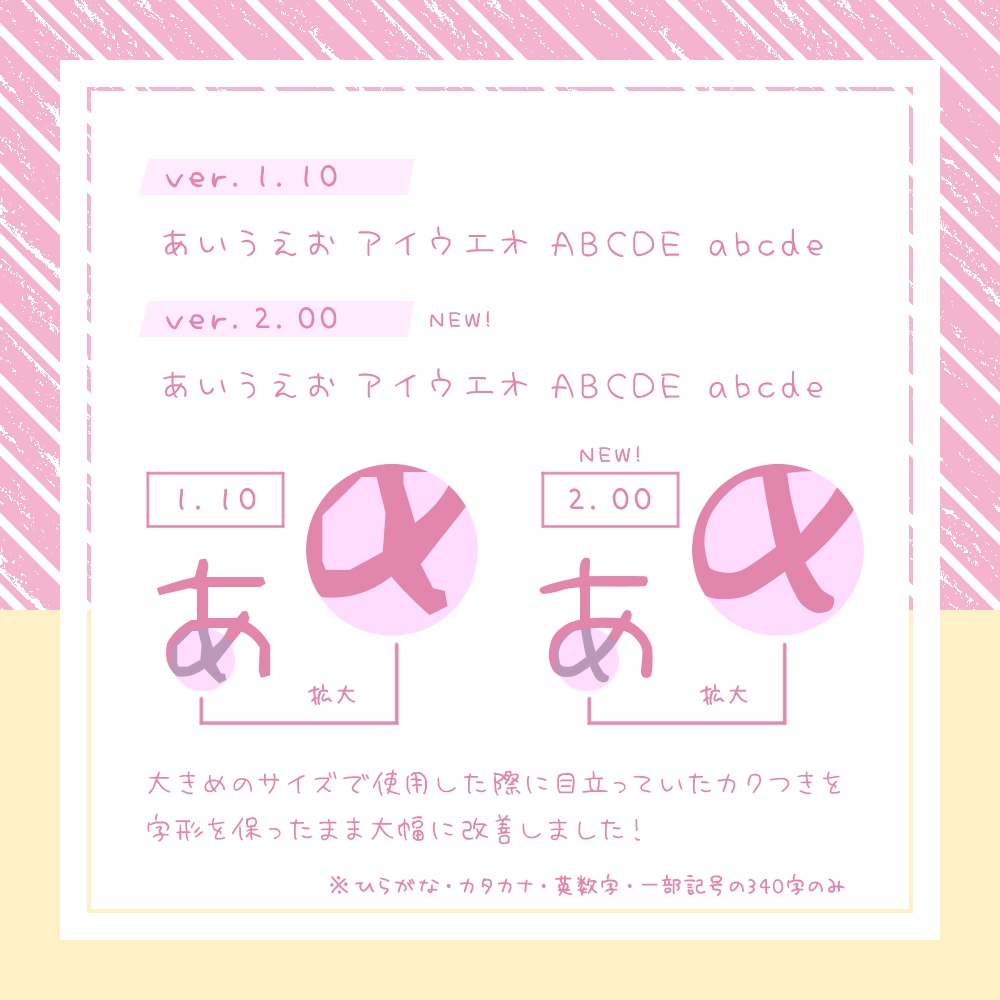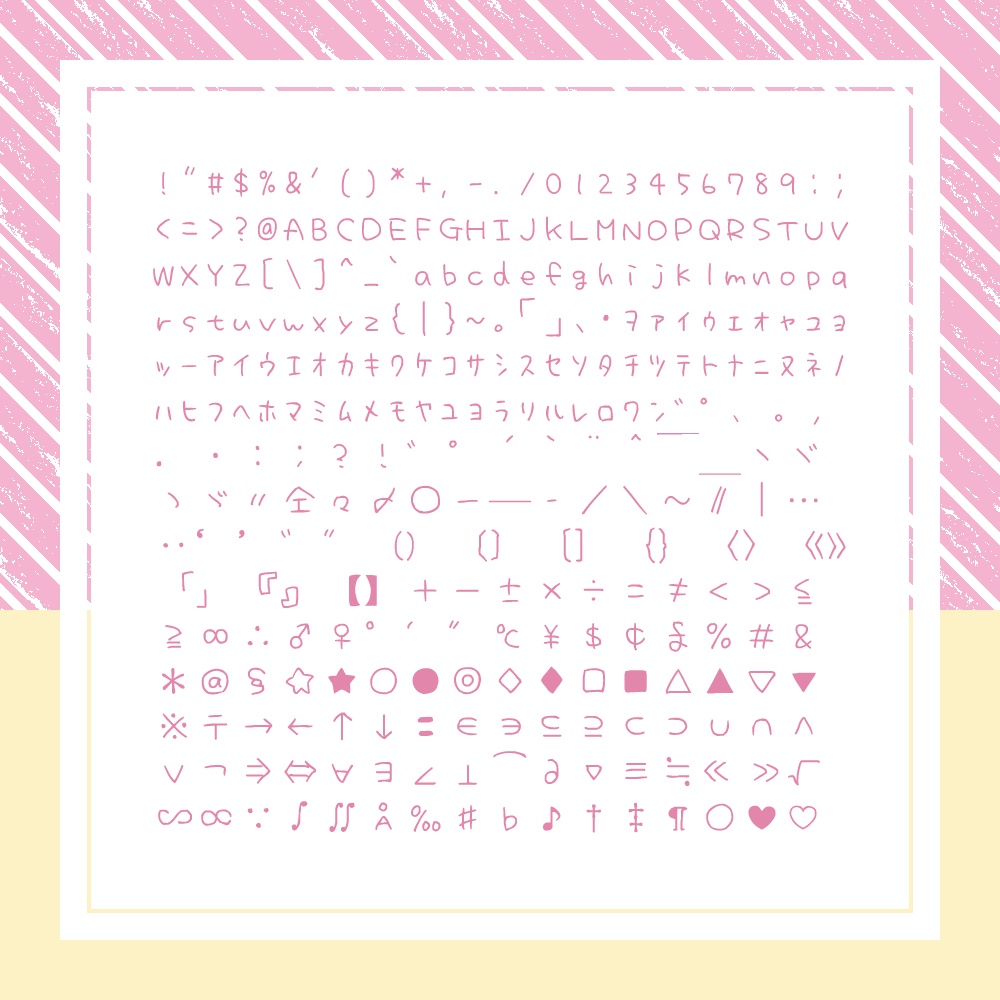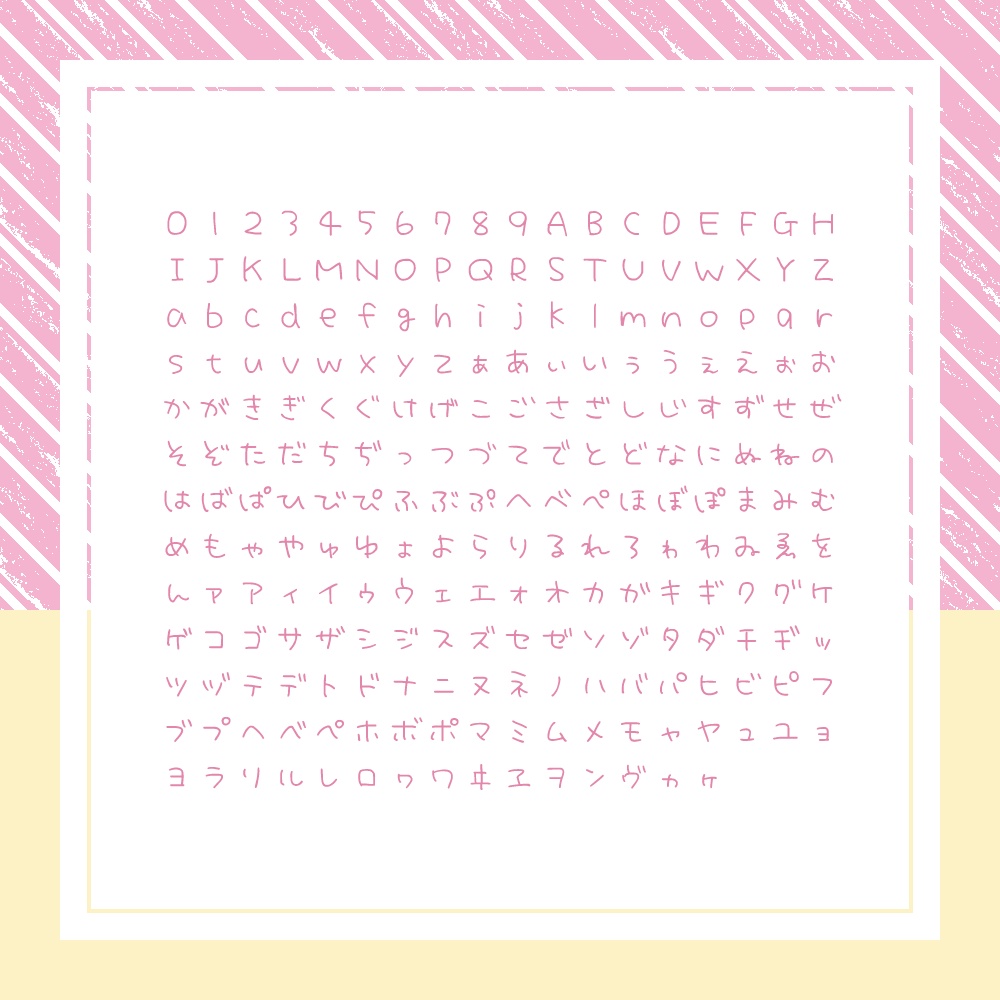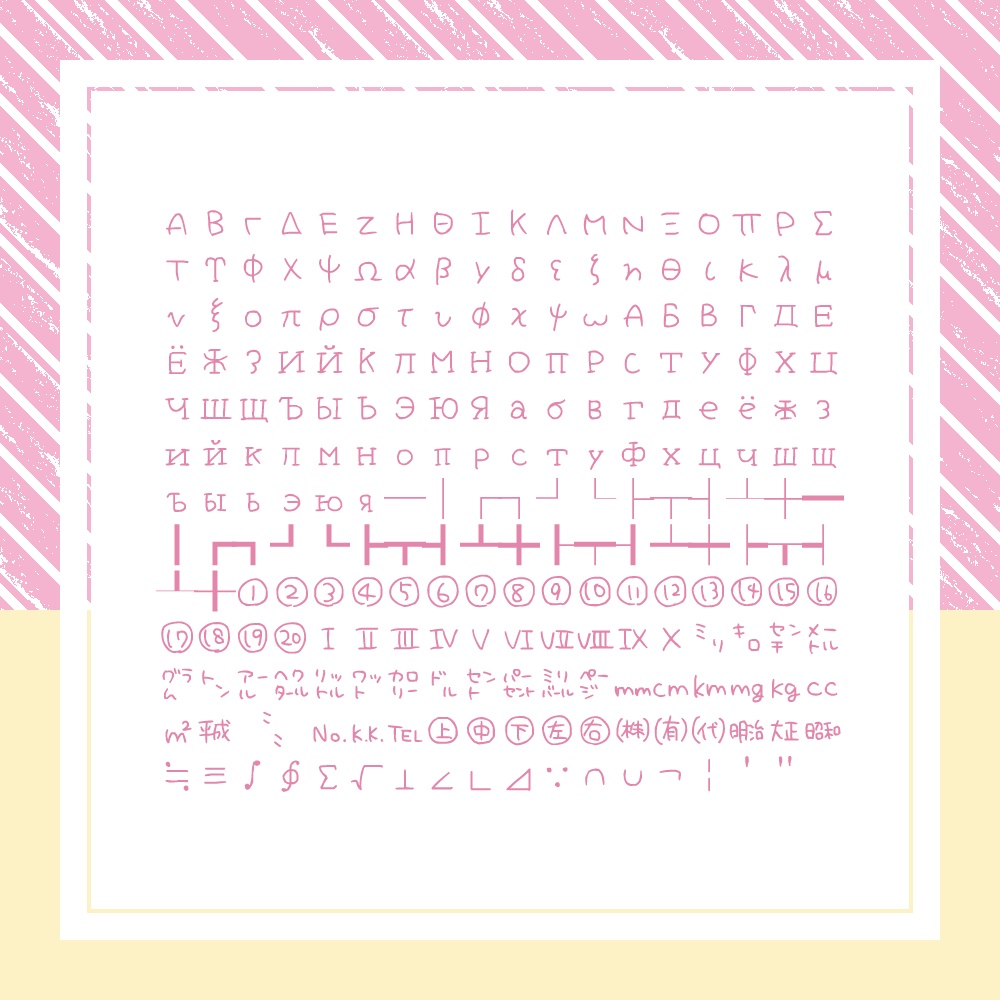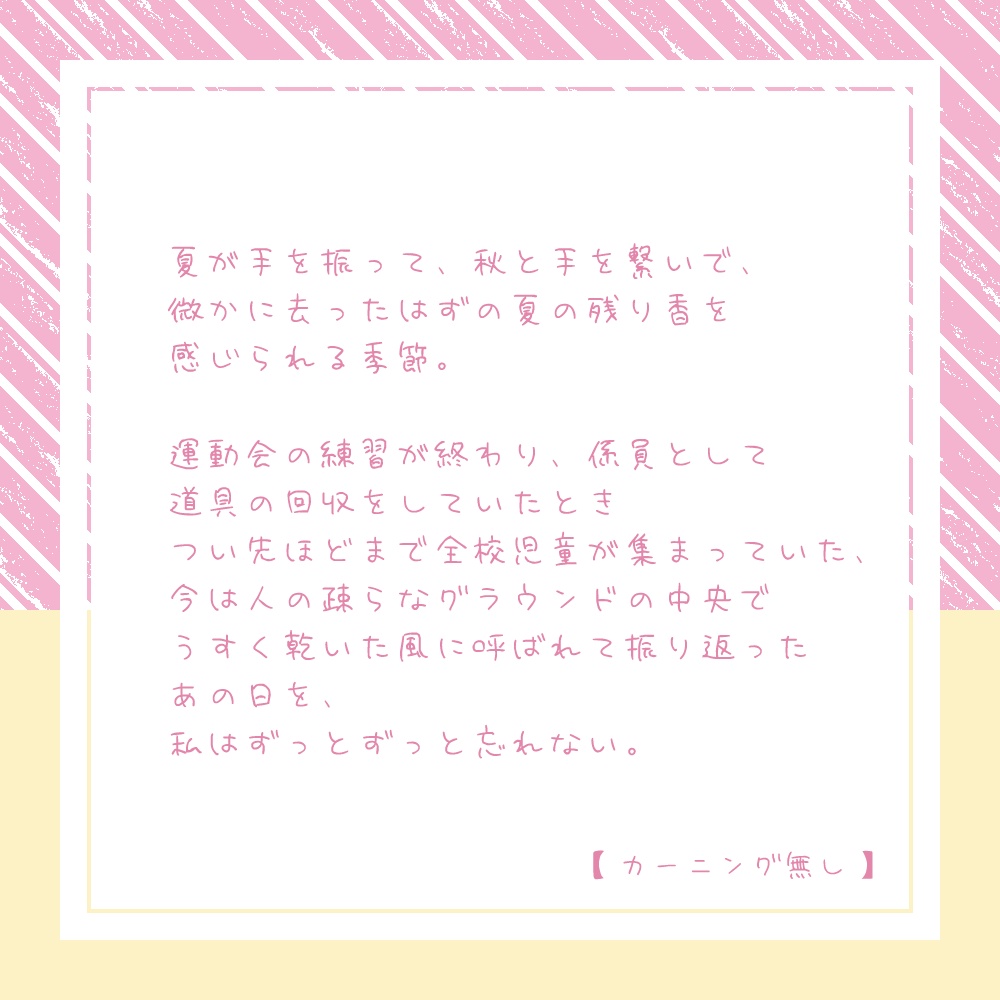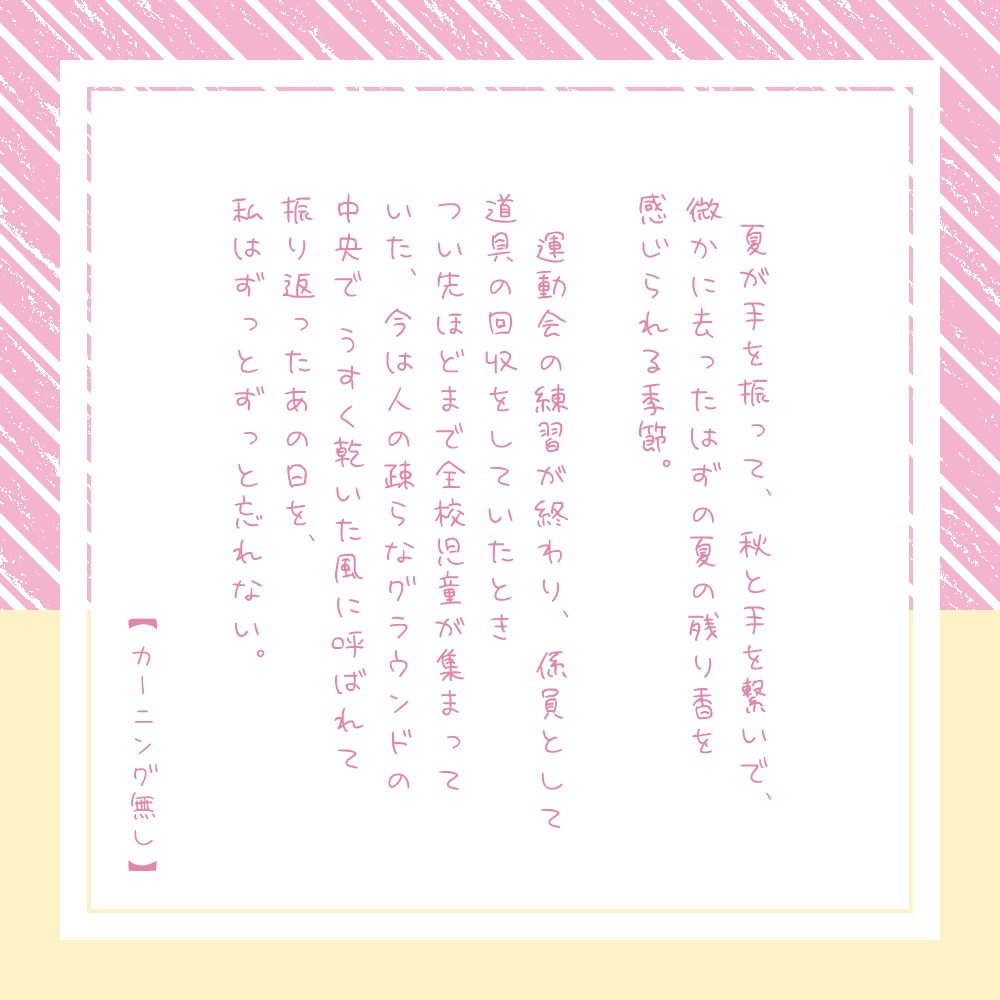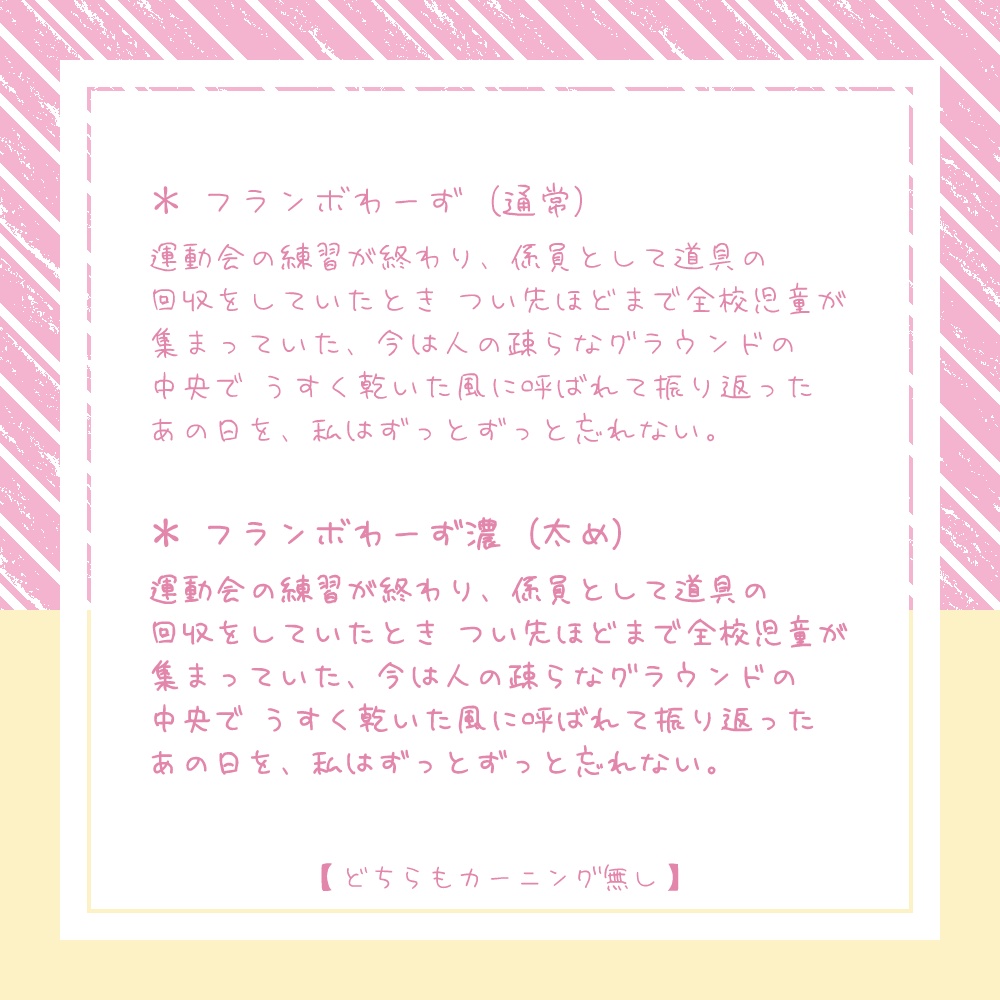
【フリーフォント版】フランボわーず2.01
こちらのフリー版は【 商用利用禁止 】です。 商用でのご使用には商用版ライセンスをご購入ください。 DL前に必ず下記URL先より利用規約のご確認をお願いいたします。 https://berrymilksugar.com/font/ ---------------- * 23.07.07 ver.2.01へ大型アップデートを行いました。 フォント名が【 フランボわーず2 】になりました。 22.07.29 に商用版にて先行リリースしていたものです。 フォントサイズ大きめで使用した場合、縁のカクつきが目立つ特性を大幅に改善。 なるべく字形を保ったまま(一部意図的に調整を入れているものもあります)、以前までは直線的だった縁部分を、自然な曲線に見えるよう調整を行いました。 今回のver.2.01ではひらがな・カタカナ・英数字・一部記号の341字のみに対応。今後不定期に対応文字を増やしていく予定です。 また、以前までは縦書きレイアウト時に専用文字として表示されていた一部字形を、通常の字形と統一しました。 ---------------- とにかく癖の強い、角の少ない丸めの文字です。エモかわ風味。 一文字ずつ手書きしており、直打ちでも手書き感が出るよう配慮して制作しました。 ・TrueType形式 / 等幅フォント / Windows11にて動作確認済み ・収録文字はひらがな、カタカナ、英数字、各種記号、ギリシャ文字、ロシア文字、JIS第1水準漢字、第2水準漢字。第3水準漢字も少し。 合計 7128文字 ・フォントサイズ小さめでの使用を推奨。サイズを上げるほどカクつきます。 (ver.2では上記の特性を、一部ながら大幅に改善しています。) 本ファイルは武蔵システム( https://opentype.jp/ )の TTEdit を使って作成しました。 ---------------- 【投げ銭版】 https://berry-milk-sugar.booth.pm/items/2197334 【商用版】 https://berry-milk-sugar.booth.pm/items/2197336 もあります。 もしもお気に召しましたらよろしくお願いいたします……!